超凡蜘蛛侠(Amazing Spider-Man)logo字体合集
这套字体合集收录了多款经典的蜘蛛侠系列字体,包括《超凡蜘蛛侠》的标志性字体、Homoarakhn Font、Speedy Font 和 Spider-Man Font。每款字体都蕴含着独特的超级英雄能量,能帮助你的设计作品瞬间提升视觉冲击力,重现蜘蛛侠漫画和电影的经典氛围,让你的设计充满活力和力量感。
The Amazing Spider-Man Font ⬇
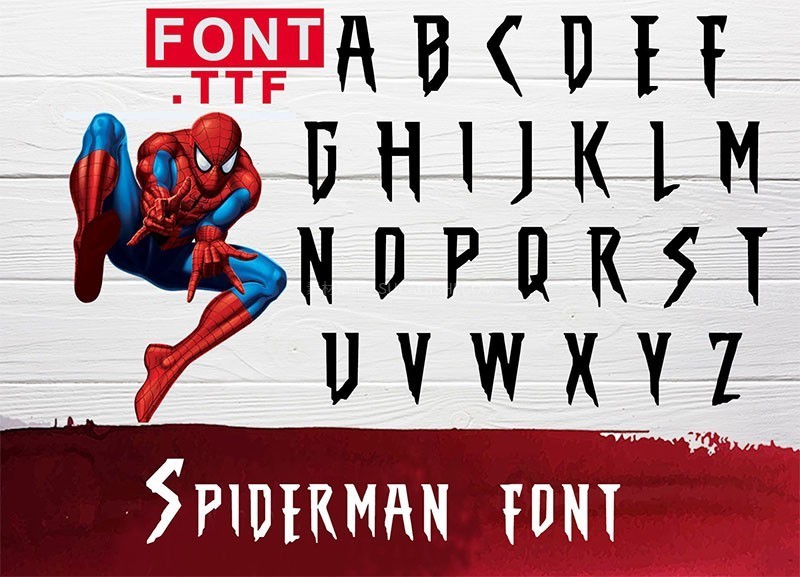
Homoarakhn Font ⬇
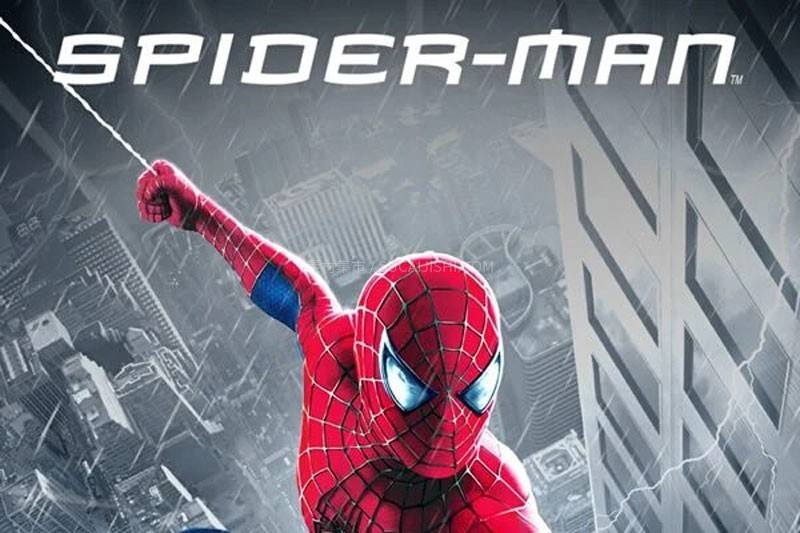
Speedy Font ⬇
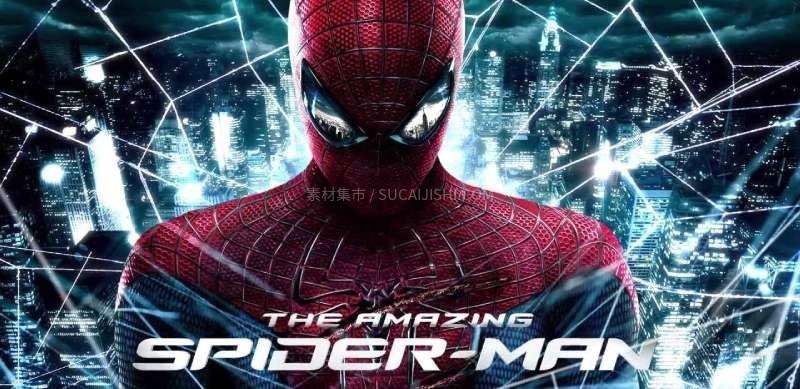
Spider-Man Font ⬇